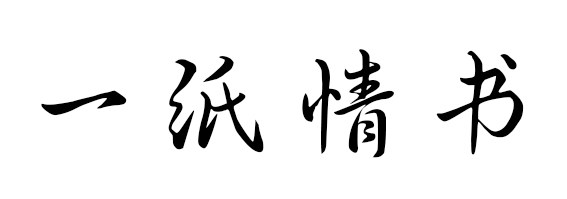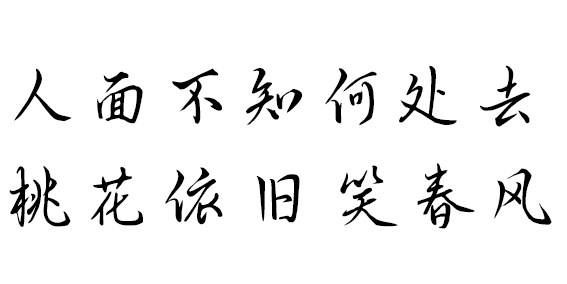
钢笔练字,硬笔书法手写体
当代大家普遍使用签字笔等硬笔来书写 ,因此造就了很多的硬笔书法体,今天我们来介绍的这款手写体在字体视界中可一键免费下载 ,你能摹仿,能够赏析,细心品位书法之美。
一纸情书
一纸情书结合了行楷的撰写标准,字型朴素摆正,字的笔画无失秀气;横画逆锋起笔,尾部顿笔回锋,以便防止钩划看起来尖锐;笔画的中区略微彭大,以绵软中合了钩划的魄力;点画干净利索,竖画苗条挺括,结束略尖,打造出秀气的笔迹 。
一纸情书